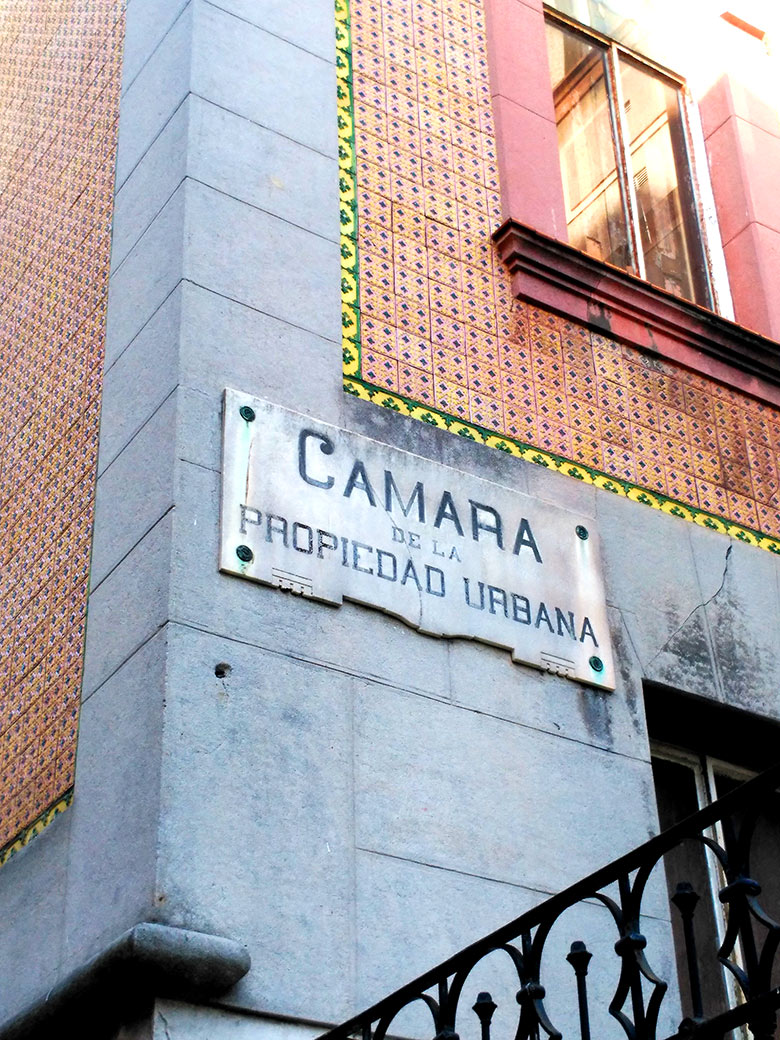
Cámara de la Propiedad Urbana de Santander
En la popular «Cuesta de las Cadenas» se encuentra el Palacete de Cortiguera, un edificio característico por su decoración que mezcla elementos montañeses y árabes. Fue construido en 1888 por el arquitecto Atilano Rodríguez Collado como residencia y consulta del Doctor Joaquín Cortiguera Fernández-Pelilla.
También acogió la «Cámara de la Propiedad Urbana de Santander». Estas cámaras fueron creadas por Real Decreto en 1907 con el fin de fomentar y defender los intereses de la Propiedad Urbana. Mantuvo su actividad hasta 1990, año en que cerró definitivamente el edificio y a pesar de que ha habido proyectos e iniciativas para reutilizarlo, sigue actualmente en un estado de abandono.
Esto lo podemos saber gracias a la placa que se aún puede leer en uno de sus laterales. Ésta tiene algo de ornamentación en la parte inferior. La tipografía es característica de principios de siglo, donde llama la atención la forma geométrica de las letras y el remate de la «C». Aún conserva su pigmentación original.